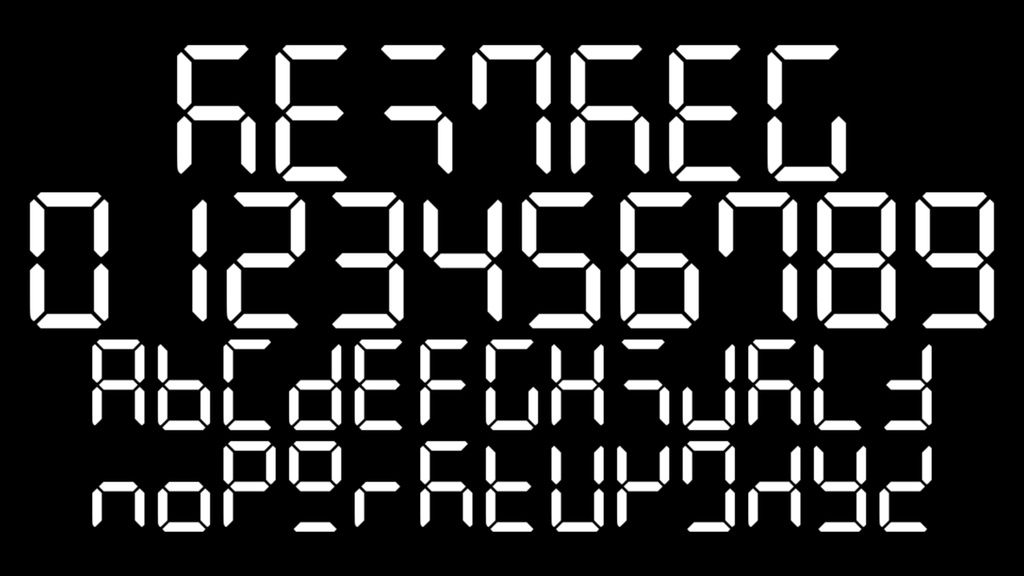
【フリーフォント】sei7seg
7セグメントディスプレイの表示を再現したフリーフォントです。
隠し機能
「U+01yy」「U+02yy」(yyは00-7Fの任意の値)の部分には、前者に7セグメントで考えられるパターン全部・後者に縦に並ぶ7個のドットで考えられるパターン全部のグリフを収録しています。 7セグメントのビットの割り当ては真上のセグメントをAとして時計回りに割り当てた後、中央の横棒にGを割り当てます。 縦に並ぶ7個のドットは真上のドットをAとして下に行くと1個ずつBCDEFGと表現します。 「01」「02」と打ったら、2進数「0abcdefg」の16進数で表現した値を続けて打ってください。 このフォント独自の仕様のため、このフォント以外の他のフォントで表示すると文字化けするのでこのフォントがあること前提の仕様にするには注意してください。